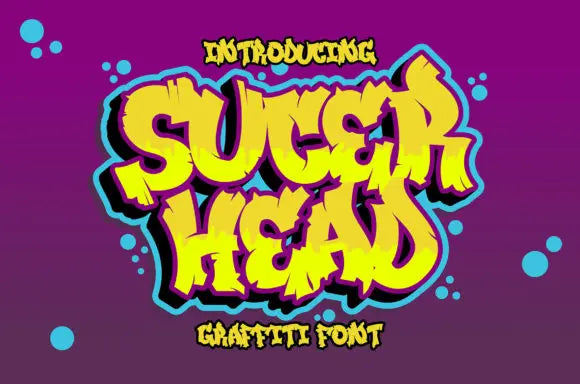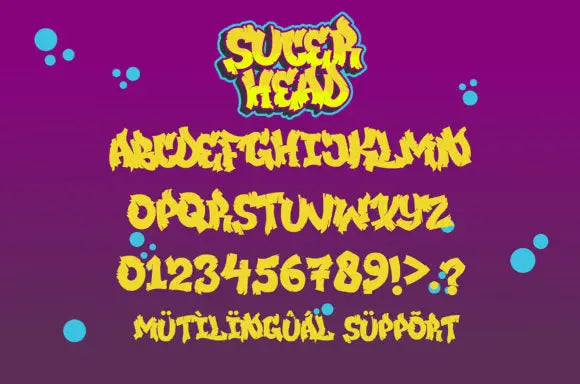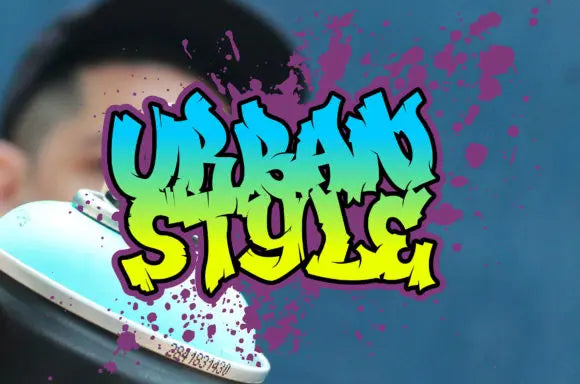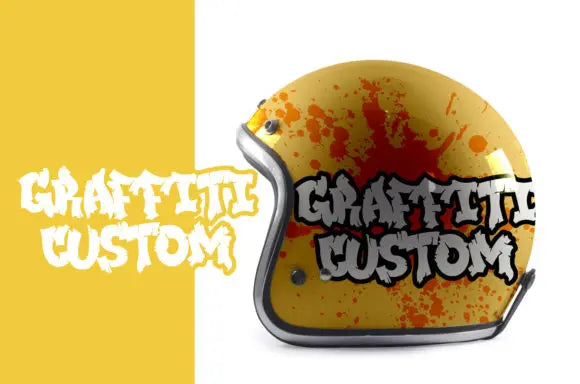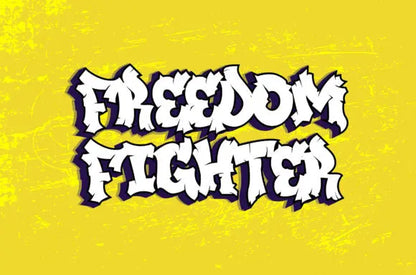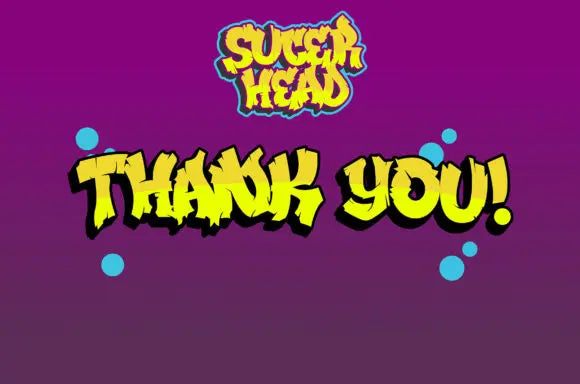
Fuente Succer Head
Succer Head es una fuente de visualización única con apariencia de graffiti. Utilice esta fuente para cualquier proyecto de artesanía, diseño de indumentaria, logotipo, publicidad, decoración de paredes y prácticamente cualquier cosa que requiera una apariencia personalizada.
¡Lleva tus diseños al siguiente nivel con esta impresionante fuente! Introduce un toque de vanguardia y personalización a tus diseños con Succer Head Font. Ya sea para un proyecto de artesanía, diseño de indumentaria, logotipo, publicidad o decoración de paredes, esta fuente de exhibición única con apariencia de graffiti es perfecta para agregar un toque personalizado y llamativo.
Con Succer Head Font, lleva tus diseños al siguiente nivel y destaca del resto.